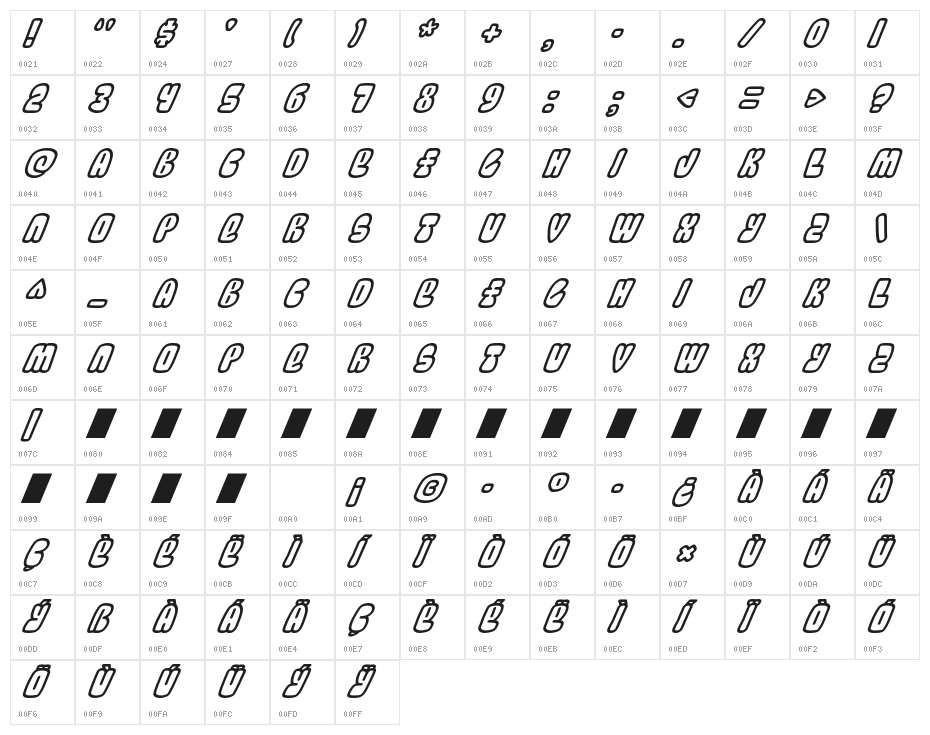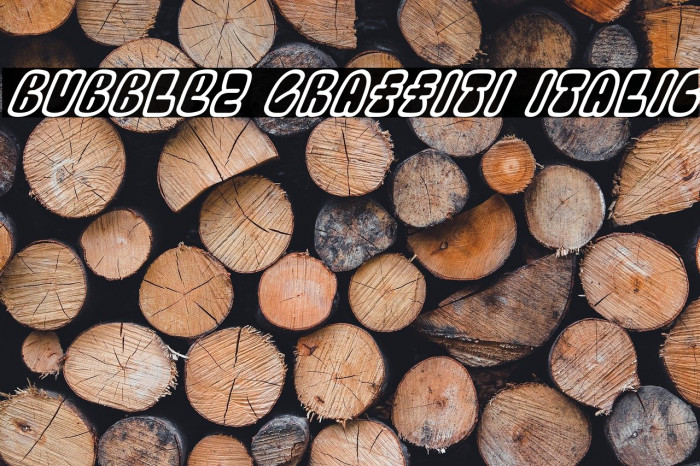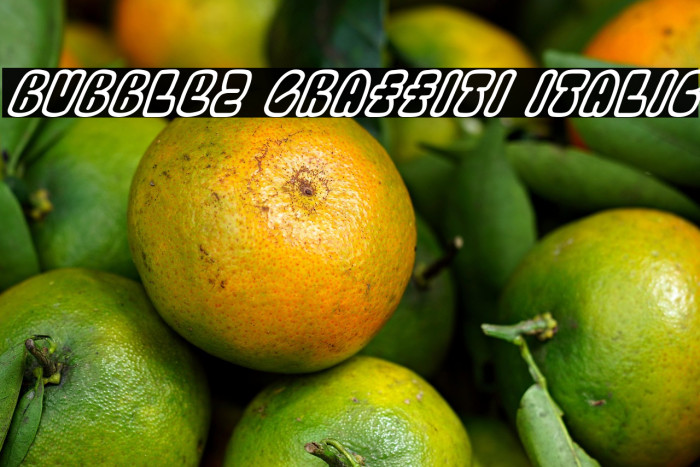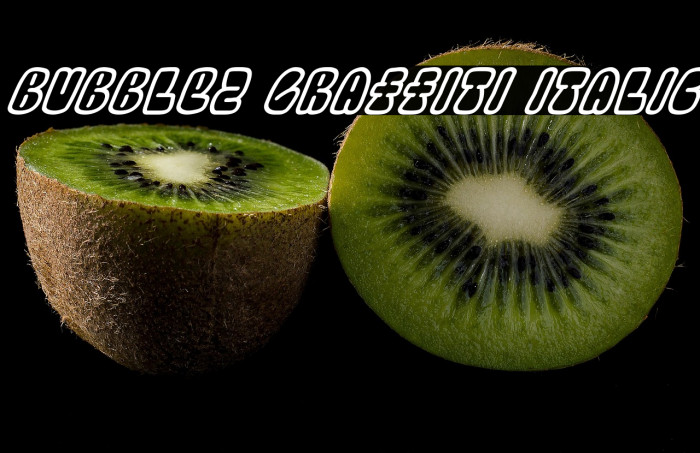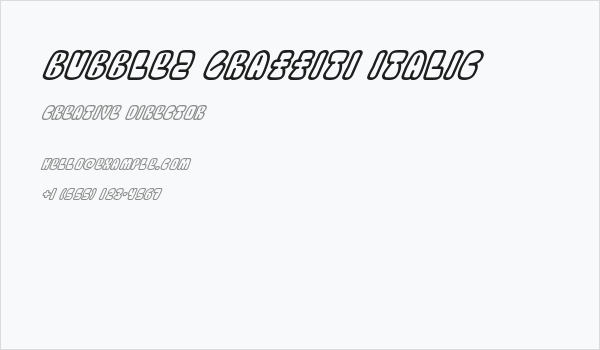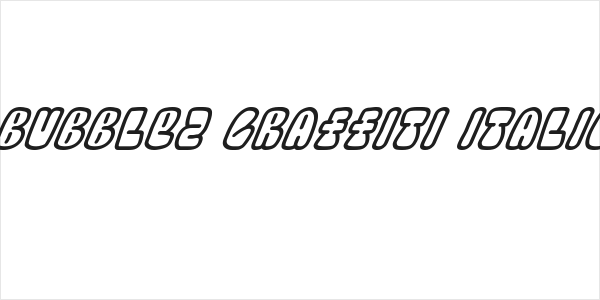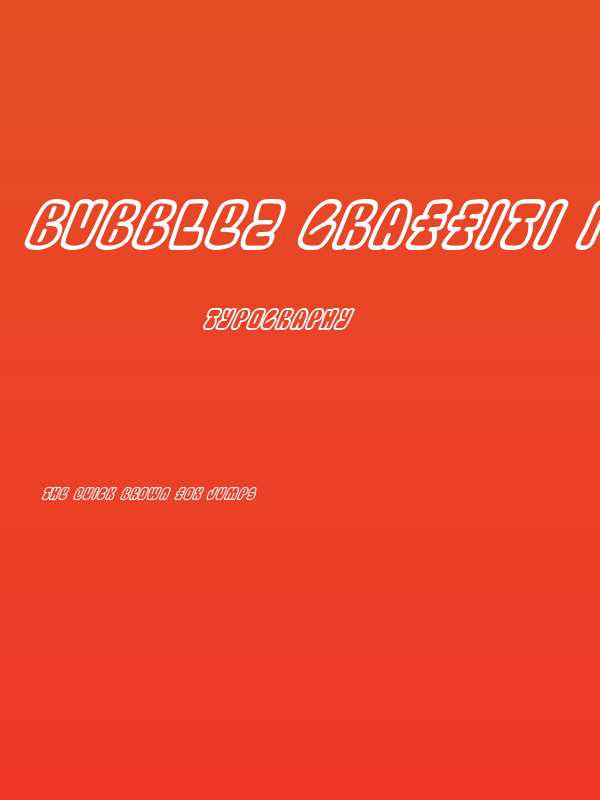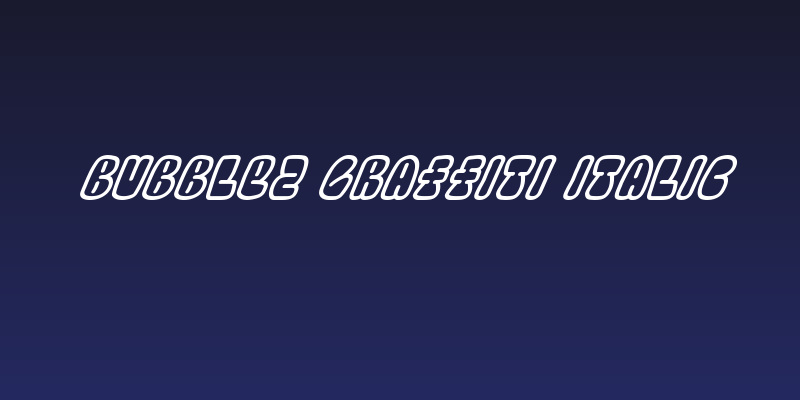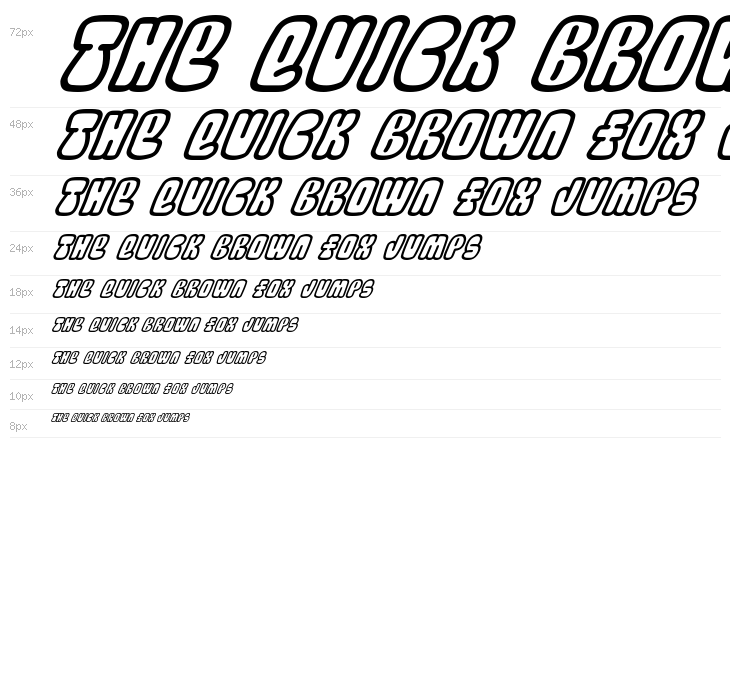
Bubblez Graffiti Italic Font
| Stile generale | Modern, Urban, Playful |
| Progetti proposti | Ideal for street art designs, urban-themed posters, youth-oriented branding, and creative event flyers. |